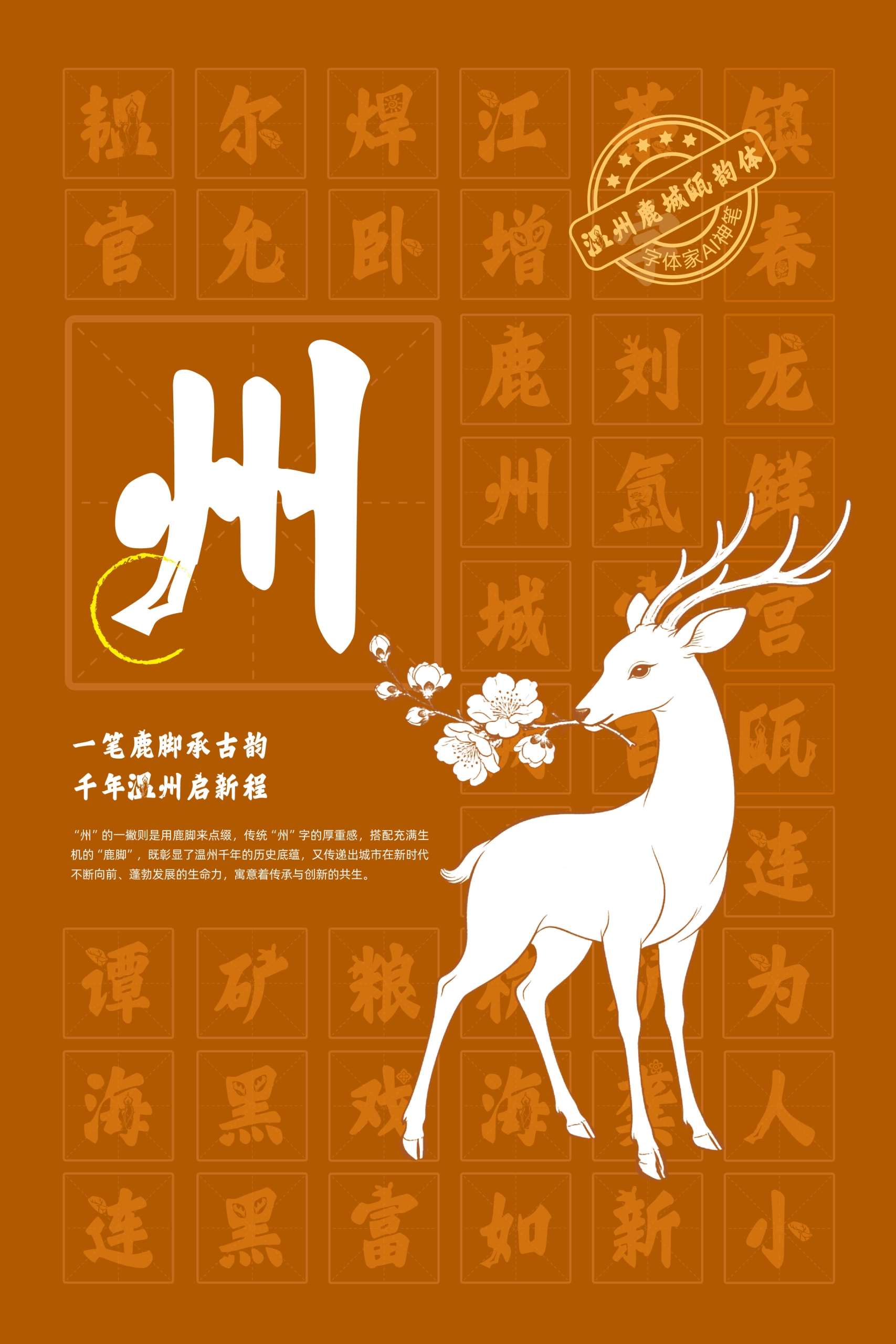
温州鹿城瓯韵体
温州鹿城瓯韵体,这款字体结构工整、笔画清晰,兼顾美观与易读性,适用于标题、正文、海报、包装、LOGO 等多种场景。字形优雅稳定,风格百搭耐看,适配日常排版与创意设计,让文字呈现更舒适、更具质感。温州鹿城瓯韵体一笔一画,皆是细节,以均衡的比例、流畅的线条打造舒适视觉体验,字形端正大气,风格简约现代。无论是商业设计、品牌宣传还是日常排版,都能轻松驾驭,让文字更有格调与力量。温州鹿城瓯韵体字体下载。
字体是文化的载体,是城市的印记。今天,温州鹿城瓯韵体正式上线!这款字体由叶根友先生原创研发,融合瓯越文化底蕴与书法艺术,兼具瓯越文化特色与现代审美,将广泛应用于影视、文创、宣传等领域,成为鹿城文化传播的专属符号!下面请大家通过观看"温州鹿城瓯韵体"宣传片了解其独特的文化魅力。该字体版权归属温州市鹿城区互联网发展促进会所有,保留一切权力,如需转载发布本字体请务必注明该页字体出处超链接,否则视为违规发布。